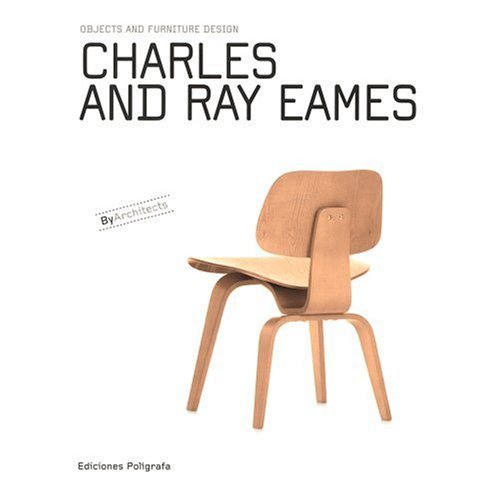
Wer kennt diese konstruierte Schrift?
Hallo, ich habe bei Amazon ein Buch-Cover gesehen und möchte gerne wissen, um welche Schrift es sich handelt. Gemeint ist der grosse Titel "Charles And Ray James".